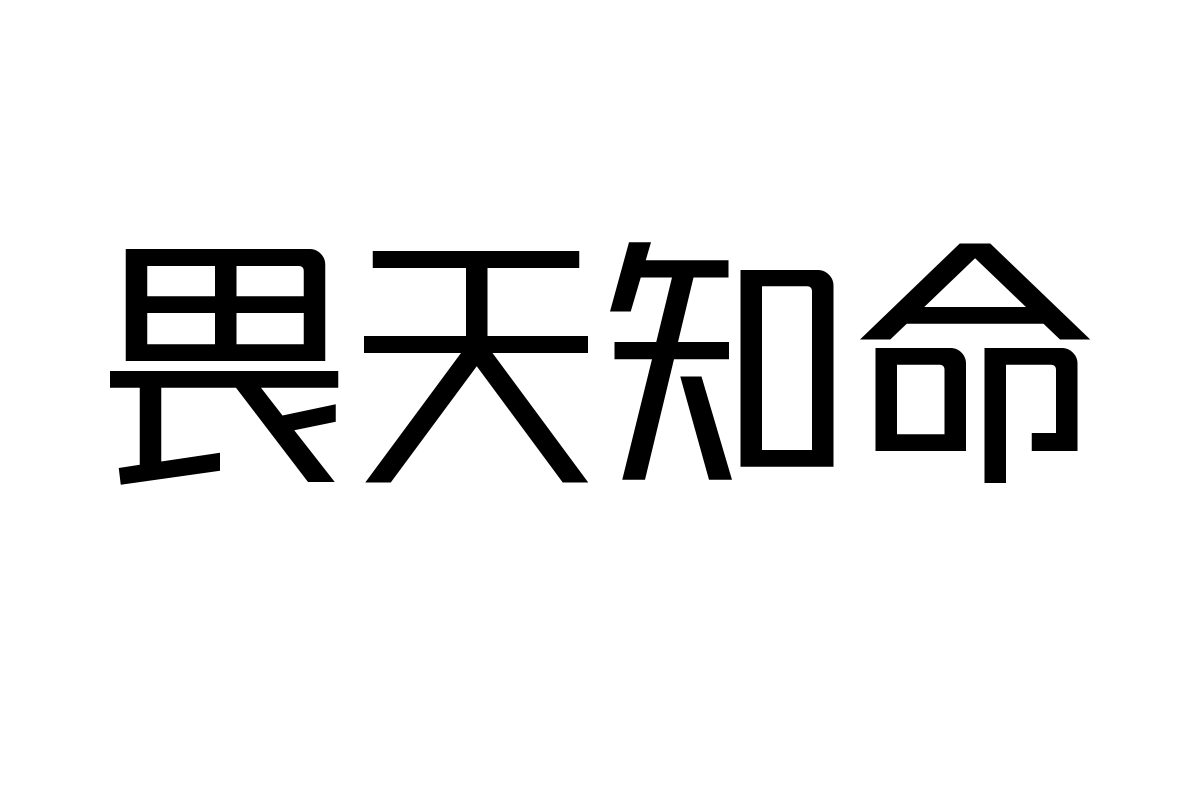
锐字潮牌真言细体是一套具有现代感和时尚气息的中文字体,适用于各种设计场景。它的特点是字形简洁有力,线条流畅,易于阅读和识别。
锐字潮牌真言细体采用了独特的笔画结构和排版方式,使得整个字体看起来既有力度又不失美感。它的字形紧凑而富有变化,无论是在海报、广告、包装还是网页设计中都能展现出独特的魅力。
此外,锐字潮牌真言细体还具有一定的灵活性,可以根据不同的设计需求进行调整和修改。这使得设计师们能够更好地发挥创造力,打造出个性化的设计作品。
总的来说,锐字潮牌真言细体是一款非常实用且具有吸引力的中文字体,适合用于各种需要强调个性和时尚感的设计项目。